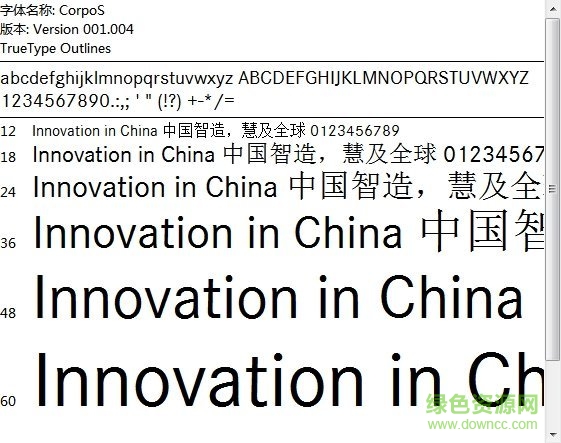
CorpoS英文字體ttf
corpos字體系列包括corpos light和corpos常規(guī)的英文字體,因其有著十分出色的印刷效果,在打印字體的使用上比較常見,是一款使用較多的logo設(shè)計(jì)自己,需要的朋友就來綠色資源網(wǎng)下載吧!
corpos字體ttf介紹
CorpoS字體是一款用于打印設(shè)計(jì)方面的字體,CorpoS字體好像是有數(shù)字和字母有改變。中文是沒有的。比較適合常規(guī)打印字體,下載后直接安裝,在word字體里面可以找到。
corpos字體造型端正,有著極佳的平面藝術(shù)效果,讓文字更加清晰醒目,便于讀者閱讀觀看,您可以使用在設(shè)計(jì)排版、廣告創(chuàng)意等多個(gè)領(lǐng)域。